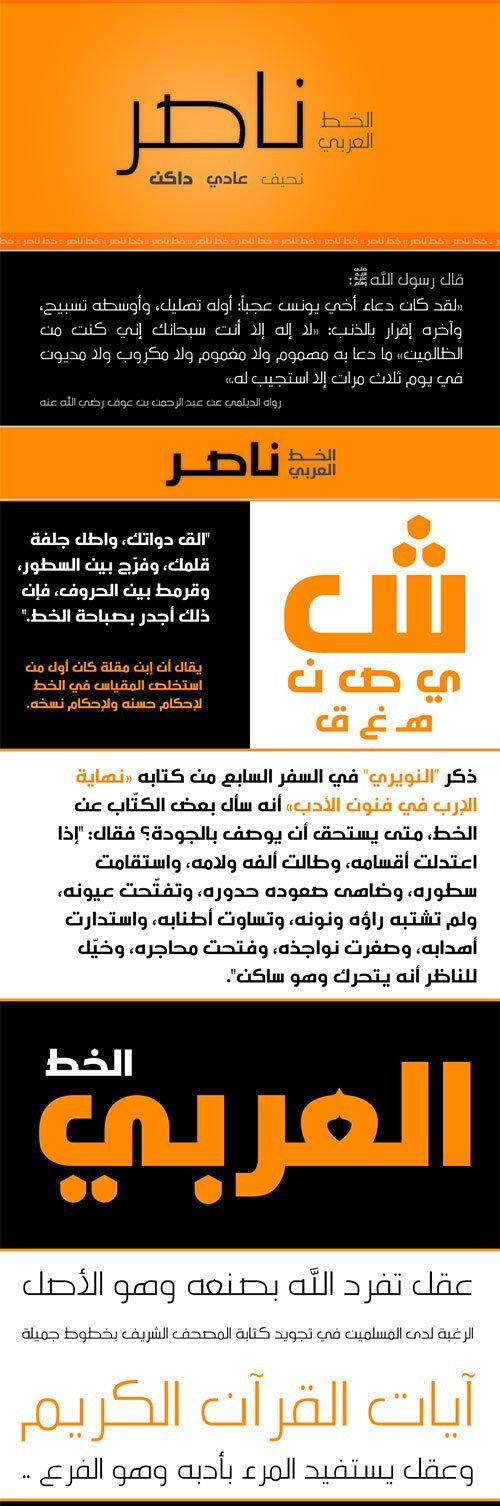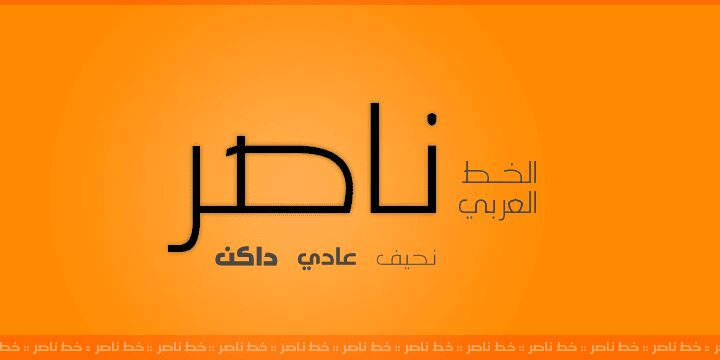
ملخص خط ناصر من Alsamman
خط ناصر (Nasser) هو خط عربي صممه إياد السمان ونشره عبر Alsamman، وهو متاح على موقع MyFonts. يتميز بتصميم حديث مستوحى من الخطوط العربية التقليدية، مع حروف واضحة وأنيقة تجمع بين الأصالة والمعاصرة. يُعد مثاليًا للعناوين، الشعارات، الملصقات، وتصميمات الجرافيك التي تتطلب مظهرًا متميزًا.
المميزات
- التصميم: حروف عربية متناسقة بأسلوب تقليدي مع لمسة عصرية، مع دعم الربطات (Ligatures) لتحسين التدفق البصري.
- الدعم اللغوي: يدعم اللغات العربية، الفارسية، والأردية، مع توافق مع النصوص القرآنية.
- الأوزان: يتضمن وزنًا واحدًا (عادي).
- التطبيقات: مناسب للتصميمات المطبوعة والرقمية، مثل الإعلانات، المجلات، وواجهات المستخدم.
الخلاصة: خط ناصر هو خيار رائع للمصممين الباحثين عن خط عربي يجمع بين الأناقة التقليدية والحداثة، مثالي للتصميمات الإبداعية. يُوصى بالشراء من MyFonts (www.myfonts.com/collections/nasser-font-alsamman) لضمان الترخيص القانوني والجودة.